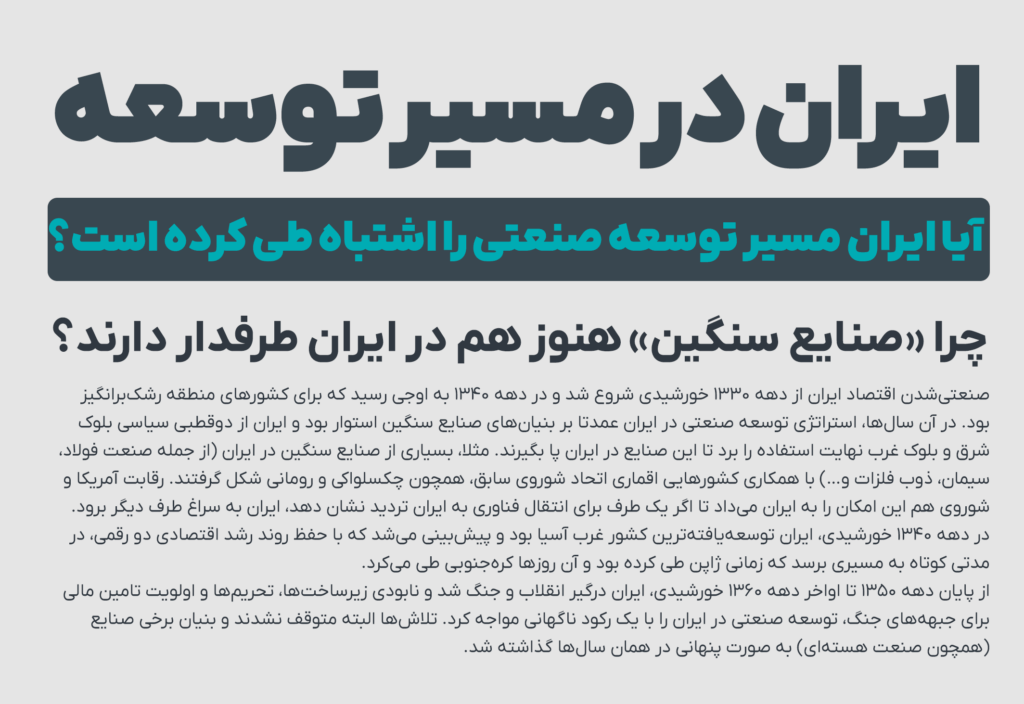
خانواده فونت ایران‌یکان
IRANYekan
ایران‌یکان یکی از محبوب‌ترین فونت‌های فارسی مدرن است که به دلیل فرم ساده، خنثی و بسیار منظم، در پروژه‌های دیجیتال کاربرد زیادی دارد. این فونت برای برندهایی مناسب است که می‌خواهند ظاهر حرفه‌ای، امروزی و بدون اغراق داشته باشند. ساختار متعادل حروف در ایران‌یکان باعث می‌شود برای طراحی لوگوتایپ‌های مینیمال و قابل اعتماد، گزینه‌ای قابل اتکا باشد.
روی فاصله بین حروف، ضخامت خطوط و فرم انتهایی برخی حروف کار می‌کنم تا نتیجه نهایی از یک فونت آماده فاصله بگیرد و به نشانه‌ای اختصاصی‌تر تبدیل شود.